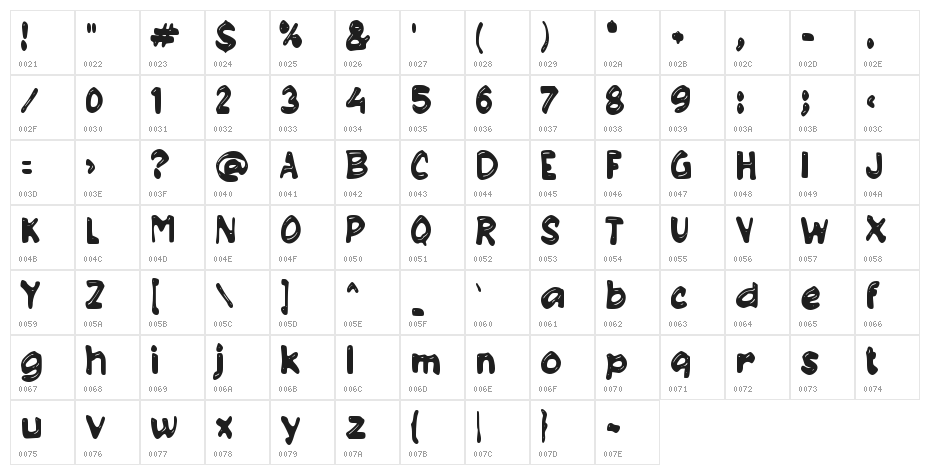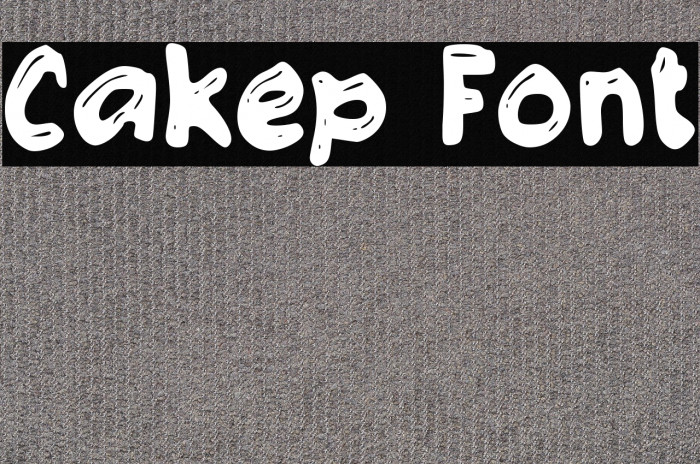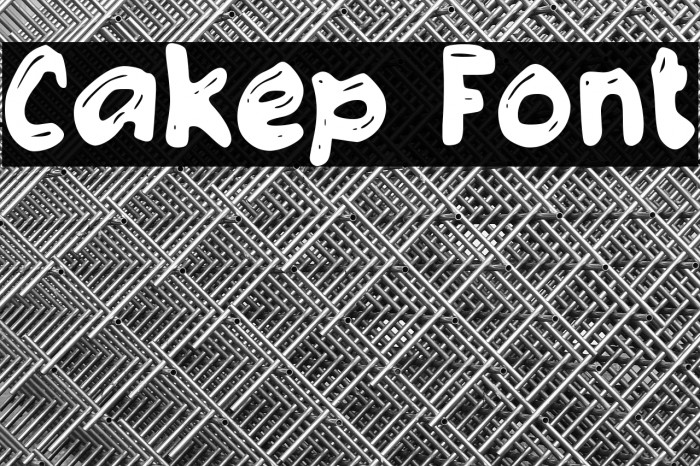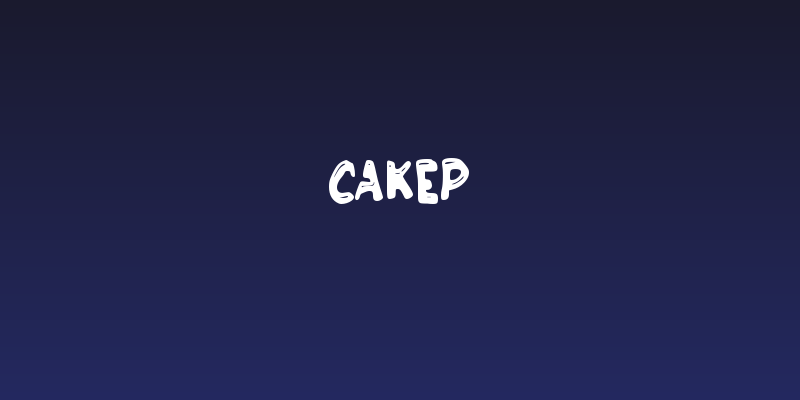
Cakep Font
| Stil general | Playful, Whimsical |
| Proiecte propuse | Ideal for children's books, comic strips, playful branding, party invitations, and posters. |